Lâu rồi không share gì nên mình quyết định share font. Dưới đây là một số font đẹp và khá phổ biến trên Wattpad, dùng làm bìa truyện, quotes, typography đều rất đẹp. Những font này dành cho người mới bắt đầu, cũng dễ gặp lắm.
Font hiện đại:
1. VL Hillda
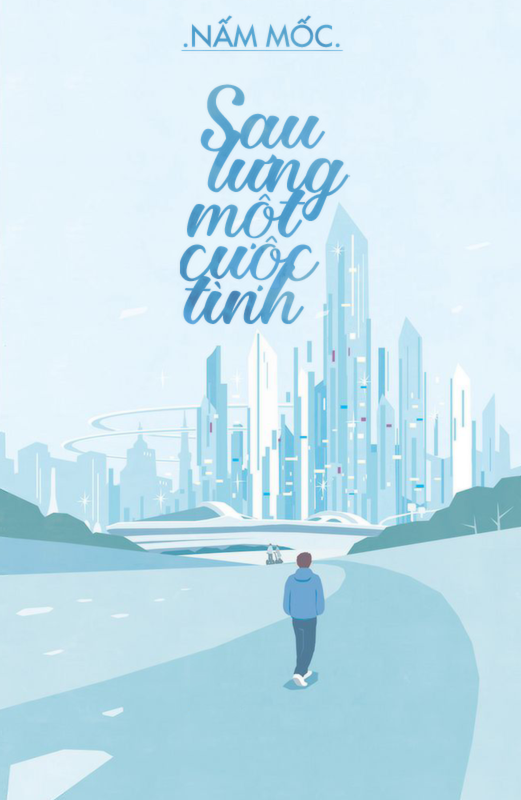
2. VL Kathya
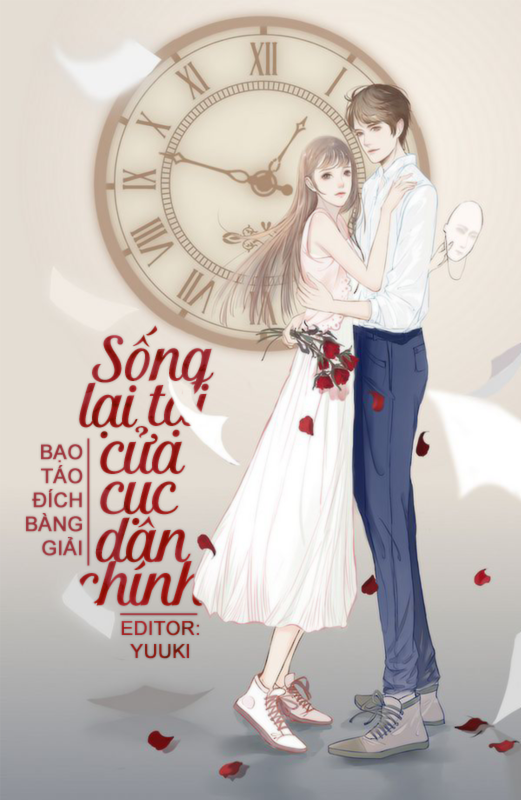
3. SVN Zelda
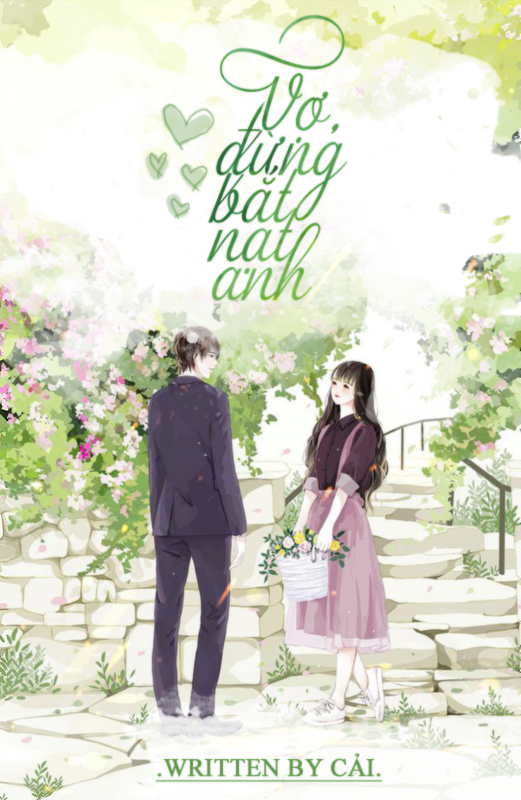
4. SVN Heroe Pro
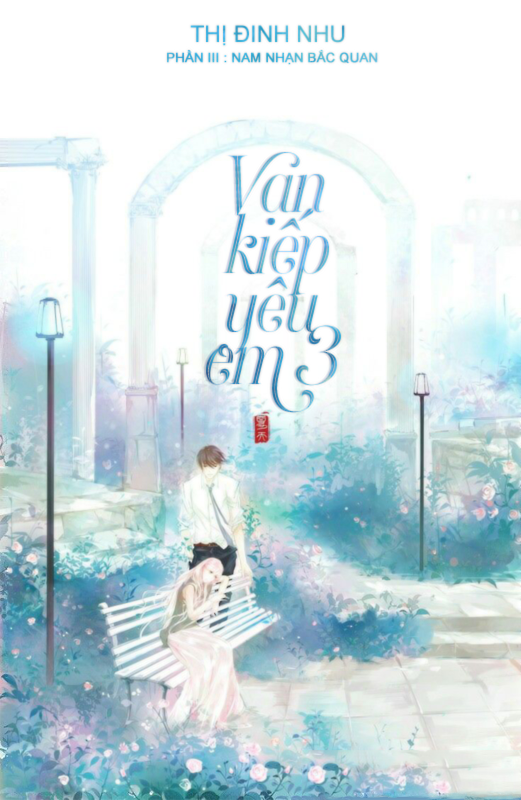
5. UVF Mishka
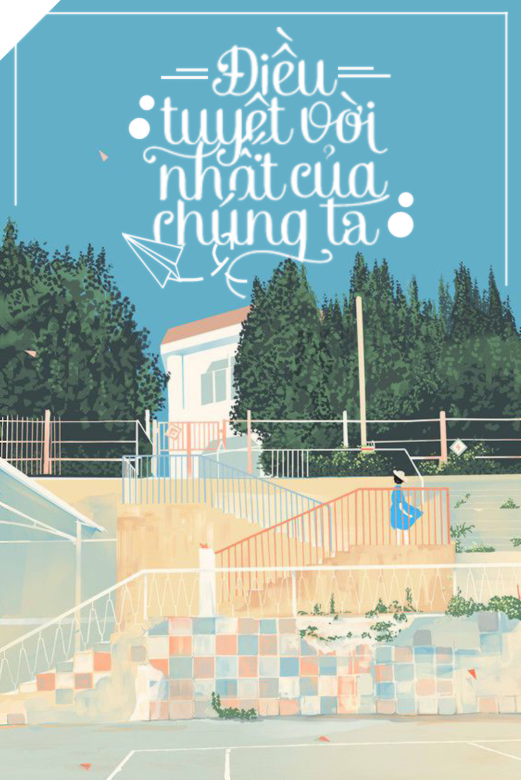
6. VL Selfie
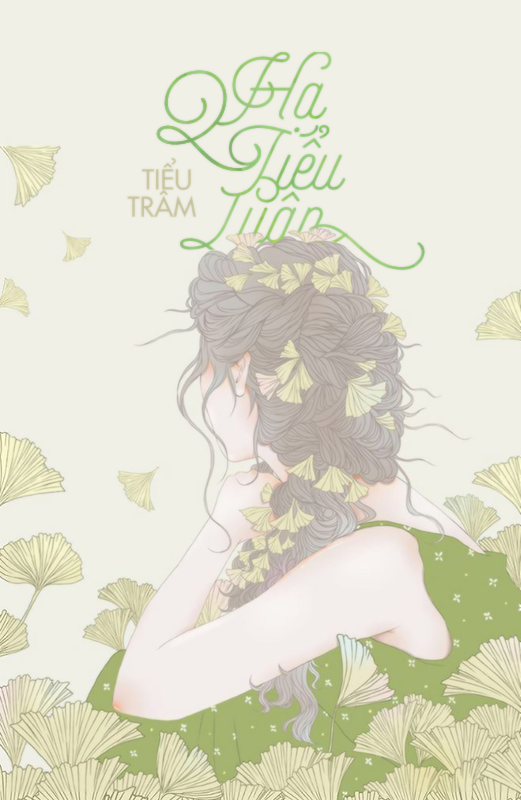
7. VL Braboll NY
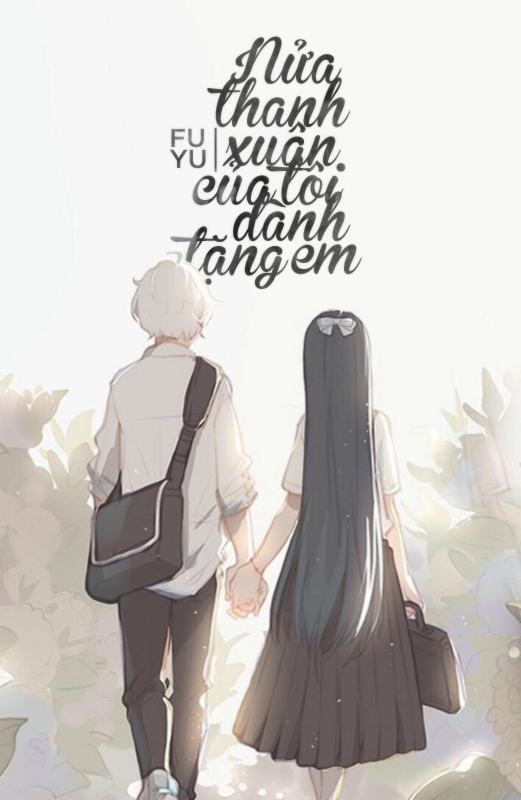
8. SVN Bellwethers
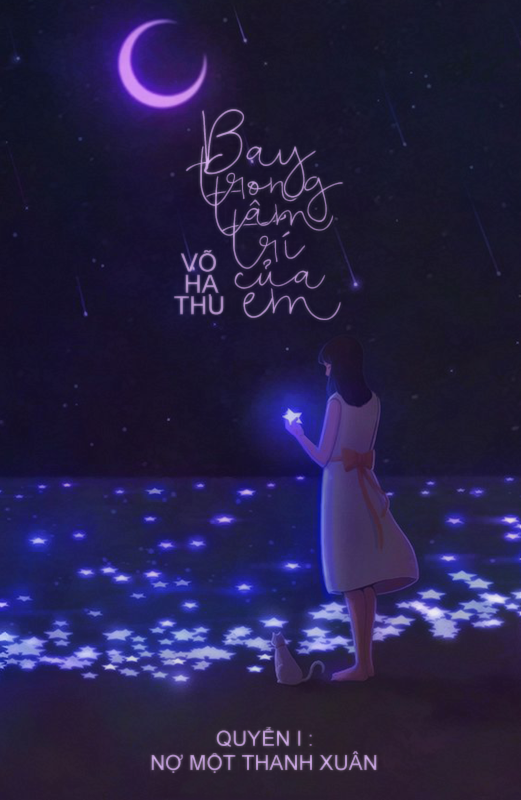
9. SVN Quarzo + SVN Quatrocentto
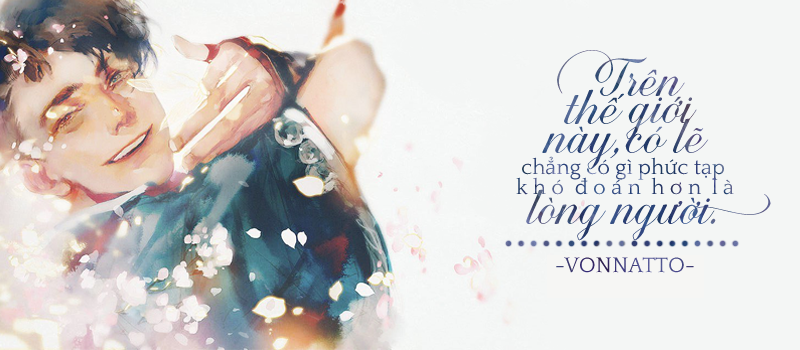
10. SVN Aire Pro + UTM Avo
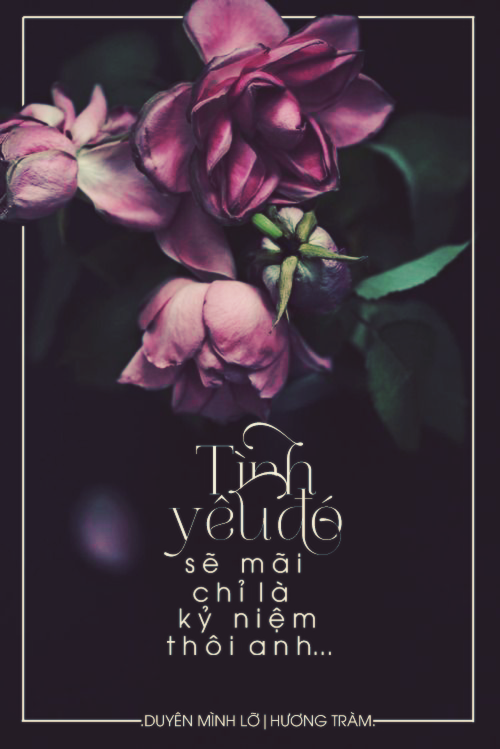
11. Iciel Humble Heart + Iciel Novecento Sans
12. SVN Coco FY
13. FS Port
14. VL Angile Script + VL Ecorpada Classic
Font cổ trang:
15. SVN Romaji Mincho
16. Linephone font:
17. SVN Desire
18. Konfuciuz
Font nước ngoài:
19. Qasmi Script
20. Signature of the Acient